一、汉字设计
从平面设计来讲,汉字无疑是人类社会有史以来最伟大最成功的设计。它以最为简单的设计元素,运用最丰富而复杂的设计手段,设计出了一件又一件恒定而单纯的"产品",并使这些产品的内涵无比丰富、构架无比完美、用途如此广泛、影响如此深远。同时,又使这些设计出来的"单元产品"具有无穷的联结方式,具有开放而递增的同构能力,具有对发展变化着的不同条件下的无限亲和性与适应性。
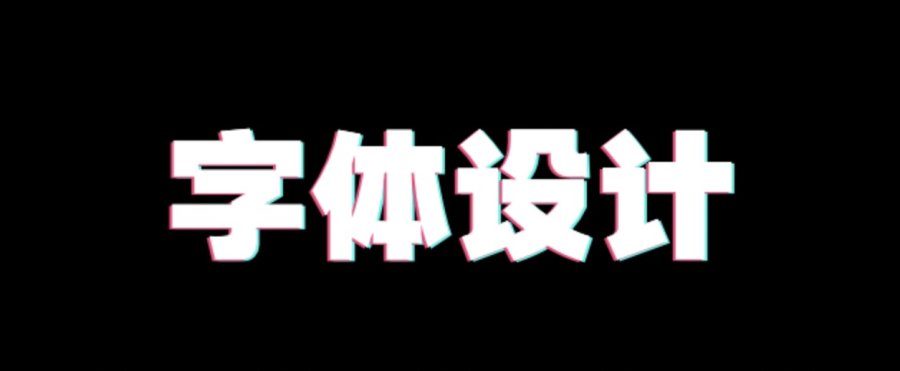
尽管许多文字学家、语言学家及其他的什么学家不停地研讨着"汉字",但是说穿了,汉字实际上只是中华民族的一种"平面设计产品"。说它是"产品",那是因为它是一种可供使用与流通的作品,它甚至还具有那么一点"一字千金"的"商品性质";而且,它的确被世界上最多的人使用了最长久的时间,并有标准的产品目录:各种各样的字典。而且它还是只供人使用的产品,世界上有猫食狗粮卖,但尚未见供狗猫用的字典和书店。说它是"平面设计",那是因为它是由只供平面设计用的点画这样的人造元件,通过平面设计的结构原理和手段,按照人类社会某种共识的理念设计出来的。而且,它有不断丰富的专门化设计工具,从刀到笔、从彩到墨等一系列独有的工具,人们还为它发明创造了专有的"载体"和"产品处理器",这便是人类最伟大的发明创造:纸和印刷术,实际上是一切文明发展的基石与最初的信息处理编码方法。它还和一切平面设计一样,可以作为思想与实体的中介与检验标准.如同我们以设计图来对照检查某幢建筑物或某件器物那样,我们也可以用"立此为据"的产品来对照那些"口说无凭"的言行。更重要的是,汉字是和所有的平面设计一样的供人"看"的,是一种只需"认识"之后便可使用的平面图形。唯一特殊的是,汉字除了与其它的平面设计相似的功能外,它自身就具备有"终极产品"的特征,并可以作为终极产品使用,完成从标识、记志、状物、抒情、审美等诸多的直接文化功能,甚至形成了"书法"这类二阶意义上的艺术门类。
所以,我们可以这样来看待汉字:汉字是出点画构成的记录人类理念的平面设计,是供书写或类似方式处理的视觉信息符号。我们也可以这样来看待许多与字体有关的中华民族特有的东西:例如,字典是汉字库,句子是汉字逻辑式,书法是以汉字为题材的书写艺术样式等等。
汉字的设计思想既高妙又单纯,它实际上只以"点画"两种元素构架而成;所谓的"永字八法"中,不同的笔画式样均可看成点画的不同位置与样式。早在宋代时,便有学者提出点也是一种画的"一画构成"理论。但汉字的结构方式却丰富无比、不可穷尽且有法度可寻。几千年来汉字发展选择的历史已证明了这一点。更重要的是,汉字的设计思想揭示了平面设计的逻辑本质,并将其逻缉方式发展到与人类的活动能作最广泛完美的联络。举例来看:"車"字是最古老的汉字之一,它实际上是以点画结构设计出的最古老的车形图样,圆形的车辐的轮、车轴与车辕的基本结构,被用点画作员简洁完美的观念记录而形成了"车"字。然而,它并不需作所谓性、数、格等任何形象上的变化而永恒地完成了一切有关"车"的逻辑表述:它不但可以记志一切如马车、牛车、独轮车、自行车、火车、汽车、电车、摩托车、登月车、光子车、太阳车等等,古今中外,以至未来理想的"车";它还可以表述某方面具有车的形式动态特征的东西,如水车、风车、纺车、车床等等;它甚至可以将一切与"车"有直接或间接关系的人、事、理表达出来,如;车水、车工、车刀、车水马龙、车过身来、行车表、车站、中夫、车轮战、车裂、车书等等。此外,"车"还可以作为汉字的设计元素,设计出遵从汉字设计规则的许多新字来,诸如:轰、轧、轨、轮、轩、辕、轿、转、斩、软、轻、轴、较、辇、辑、轳等等。由此而引发造就的各种词句,那简直不可胜数、难以枚举。它们不但有"轿车"这类当代车名,也有"轨迹"这类专用术语,更有"辅佐"、"转化"、"轩昂"、"轻率"这类无所不在的词汇,甚至有"轰轰烈烈"、"车站再大住不得"这类俗白。也许我们不难发现,任何古今中外、甚至可以想见的未来场合中.只要有中国人的地方,就随时随处会有与"车"有牵连的"设计产品"之使用。
其实,每一个汉字都是这样的"产品",它们共同构筑了中华文明,迁延并光大了中华文化。其实,最初的汉字就直接称之为"文",中国文字统一后的第一部字典便称为"说文",在这部辞书精典中也明确地将汉字的结构规律与法则总结出来,并明确地指出"交画为文"的道理。而"文明""文化"这些词汇,所总结的正是汉字那种"无物不明、无识不化"的特殊功能。在五千年的发展过程中,汉字已成了最完善的"视觉平面信息记录体系"。有些不究此理、不明此义的人却违背这些,要搞什么"走世界共同的拼音化道路"的"汉字改革",成立什么文字改革委员会,他们实质上是想取消汉字的视觉平面结构信息特征,他们不明白汉字多种写法那统一而同一的构成规律,以减少汉字笔画来"改造"汉字,甚至以错字、别字来"规范"汉字。于是,出现了繁简二体,由于繁体字能包含代替简化字,而简化字却不具有包含代替繁体字的功能(至少在简化字出台之前一切汉字典籍均以繁体字留存),因此,这实际上是在每个字少了几笔之后而多制造出了几千个常用的汉字,造成了汉字体系的混乱化和复杂化,试看那越来越厚的字典(必收繁简两体),便不难明白这种错误的严重。这给汉字的规范化带来了许多困难的工作,不利于时空双向的开放改革与文化交流。要不然,在以开放改革为基本国策的今天,那个标榜改革的"文字改革委员会"何故要改称为"文字工作委员会"呢,以简化为先导,以取消为目的的"汉字改革"正是那种资产阶级民主革命和民族文化虚无论下的行政命令之产物。错了,改过来就是。汉字体系的宽容性的确有许多"文字工作"等待"文字工作委员会"去工作。
众多的以汉字书写的文明,对于中国人的造就,也许在今天会进一步得到发展与辉煌,汉字那平面设计中所包涵的精髓,也许正值得每一个"设计家"们学习、继承与探索。
我永远为汉字设计而感神圣与自豪。
二、铜钱设计
我经常会有一种想法,觉得世界最高的设计大奖应当授与中国古代那位替秦国设计铜钱样式的设计师。
也许我的想法并不无道理。就单件设计所使用的长久、所造就的产品数量之众多,再从使用这些产品的数目与人次,以及这一设计迁延时间的长久,这一设计思想的发掘与设计观念的拓展,这一设计导致的丰富文化内涵之发现与应用等等用以衡量设计成就的诸方面来看,可以说绝无出其右者。那么,如果要在世界范围内评选某一设计大奖的话,自然是非此莫属了。
中国是最早有货币的国家之一,自夏代开始,各样的天然货币与人造货币相继出现;商、周以降,各类货币的设计足以向我们展现出那几千年中高超而丰富的设计水平。许多定型化的货币设计样式一直影响到后来中华纹饰的发展与文化的形成。然而,这些丰富而复杂的设计没有一件可与后来的铜钱设计相比。秦代的铜钱,选择了最为简洁的里方外圆之图形,完成了最完善的使用功能与最广博的教化功能。
可以毫不犹豫的说,对于圆形与方形的掌握,是人类最初对抽象图形认识的最重要的升华阶段之—,是由点、画这种基本笔画上升到由笔画构成的基本图形(由线性发展到平面)认识的标志。在中国原始社会的彩陶纹样中,基本的纹样除了点画曲线之外,趋于规整的便有三角形、方形与圆形纹样。这些纹样通过巧妙的组合,形成了丰富的纹饰。然而,要将方和圆作为设计元素与设计思想来运用和表达,还有赖于更进一步的对抽象设计元素的领悟与把握。当人们明白了"不以规矩不能成方圆"的道理,明白了"圆使动、方使静"的规律,甚至能以"天圆地方"、"方正圆滑"等文化观念与感受模式来量度"方"和"圆"时,这样的设计才显出了无比的高妙来。
钱是要使用与流通的,全世界后来所有的硬币几乎都归结到圆形的设计上,而只有中华民族选择了有方孔的圆形作为硬币的终极样式。以绳索贯穿着的钱币,自然便于计数与携带,而作为钻孔术来讲,铸造方孔要比钻圆孔容易得多。中国钱的这一设计,自然有着无比丰富的文化要求,而使得它要"舍易求难"了。
正是由于这种"舍易求难"的工艺设计,铜钱的设计也自然在使用功能与文化亲和能力上才具有了更多发展的可能,穿孔的钱更利于携带与计数。而方形的孔与圆形的钱又可同时更多容纳与图形有关的其它社会文化观念,例如流通与稳定这种钱的基本功能、圆滑与方正这类人的社会品格、周边与中心这类位置观念正是如此,才会出现了"孔方兄"这样的钱之称谓,使得钱也随孔夫子般地姓起"孔"来,适应了儒家倡导的文化精神。随之,中国的财神爷才有可能得了个"公明元帅"的名字。而"钱心方正,财神公明"这类的联语才可以从更广的文化观念上寄托着人们的希望,造就着人们的品格。
如果我们再进一步考察中国老百姓对许多日常用具的设计,我们也会发现不少"舍易求难"而"以应方圆"(规矩)之处。中国人须臾不离的筷子,老百姓生产生活最常用的箩筐簸箕之类用具,大抵作成一头圆一头方的形状,都是最常见的例子,也都是在设计制造上舍易求难的典型,否则,那些被"改造"了的现代方便筐、卫生筷之类就不会不继续这种耳目能详的造型。我们再看看当代无数的商标等标识的基本造型,大体上还遵循着以方圆等基本图形的相互对比、穿插或包含的基本路数。而这些,正是中国铜钱的基本设计思想。
可以毫不夸张的说,中国铜钱的设计成功正是中国设计师们觉悟了平面设计的基本原理与法则的结果。这一设计原理是永恒的。
三、如意设计
恐怕没有一个设计题目比"如意"更困难了,恐伯也没有一种设计比"如意"的设计经历过更漫长的探索和更广博的取舍了。而且我认为,没有一类设计比"如意"设计定型化之后的"成品"能更完美巧妙地解决设计命题的要求了。因而我们可以毫不夸张地说,难能可贵的如意设计简直是一部浓缩的中国设计思想史与中国设计教课书。
从典籍史册来看,至少在晋代已有关于"如意"这种器物的记载与描述,而在历代的文献中,"如意"不绝于书,但其形制功用,却始终未能如一。大体功能是使用,可替圭板、可作搔痒、可捶腰背、可供玩赏。大致形制是长形有柄,可直可曲。直到明清之际,"如意"才成为定型化器物,主要功用是赏玩。其形状为曲线形的柄l头、中、尾部有不同大小形状的曲线形雕饰,或拟云头、或拟灵芝。材料有各种骨木瓷玉铁,工艺含各种雕缕鎸镶贴,而其上所装饰的纹样图形,则可说是从文字到图画以至纹样几乎无所题材样式不能包容了,其供赏时的陶教作用,自是可想而知。
细论起来,以"如意"为题的设计要达成定型化样式几乎是不可能的。中国老百姓十分明白"有钱难买心中愿"、"匹夫不可夺志"、"心比天高"之类的道理。西方人也将"自我实现"当成人类最高层次而不可完全实现的心理需求。然而,"如意"的设计似乎在攻克着这样一个难题。从最初的功用看,如意似乎在满足着使用的功能要求,但进一步思考起来,它的所有功用,实则是更直接地通过对身心的作用来达到一种身心的满足。而后来它成之为供赏佳器,也正是抛开了对实用的追求而直接作用于人的把玩和因此产生联想而获得的身心满足有关。
中华民族远古的生存方式与生产方式——农业生产的方式造就了中华民族选择双眼变化视场的基本视觉习惯。并希望通过目光的变化停滞来对视觉对象作出由表及里的判断。从彩陶纹饰、青铜纹饰与后来众多的装饰纹样之结构与方式上,都不难总结出这样的特征来。而如意的基本造型正是这一具体视觉特征的理性表述:整个如意无论从哪一个侧面正视,其基本可视范围正是一个与双眼视场相若的区域,而如意的每一个构成部位,正是一个从上至下的变化着的、并停顿在能控制整个视场区域位置上打量的观察结果之示意图形。每一个中国人在注目欣赏一件对象时,文化导致的视觉方式与视觉心理都会引导着他们从上部某一角的停顿而弯曲地到达中心的停顿,继而反向弯曲着抵达下部另一角的停顿。将这视线与停顿以曲线与曲面表达出来,恰恰是一个如意的基本图形。实际上,从彩陶纹饰那种基本走向与转折停顿的纹饰,从青铜纹饰中那纹样起伏变化与各刻画部位的不同侧重,从秦汉漆器中那些飘动的云气纹,隋唐装饰纹样中那些卷草纹,以至于许多后来民间纺织、陶瓷等工艺的装饰纹样处理中,甚至于太极图的基本结构方式中,实际上并不难找到一个抽象出来的"如意形"的基本纹样单体。因此,每一个人都能从这种基本样式的造型中得到心满意足。另一方面,每一个人都可以在不同的如意中选择不同的材质与制作手法,从至为昂贵的金玉宝石镶嵌的翡翠到最为普通的竹木,从最为精细的雕镂楼打磨到几乎未经加工的树根枯木拼接,在材质与工艺上可以制造出富贵、高雅、清贫、孤傲等等备种各样的感觉。
再一方面,更为丰富多样的表面饰纹又可以表达每个中国人的理想与追求。诸如祥云、嘉禾、瑞兽、珍禽,以至于三星高照、四季花木等等,使得许多观念得到形象的表述与逻辑的演释,给与了每个人思想感情上的快慰与满足。
正为其如此,它才被每个中国人称之为"如意",而成了最有代表性的典型物品。成了中国设计中最有趣而引人深思的设计之一。
在当代设计的学习与探索中,也许这些不同的中国设计,会给我们带来不少的启迪。